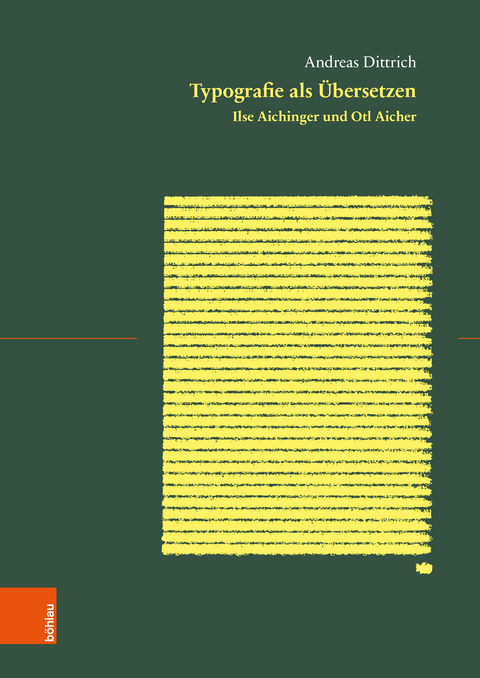
Typografie als Übersetzen
Ilse Aichinger und Otl Aicher
In Otl Aichers Gestaltung der Texte Ilse Aichingers erscheint eine Typografie, die übersetzt.
Das Erscheinungsbild von Ilse Aichingers Texten wird seit 1965 maßgeblich von der typografischen Gestaltung des Bandes »Eliza Eliza« geprägt, die von Otl Aicher eigens entworfen wurde. Dieser Band steht im Zentrum der Untersuchung, in der der Frage nachgegangen wird, wie sich Text und Gestalt zueinander verhalten. Auf Grundlage der in diversen Archiven überlieferten Dokumente wird die Freundschaft der beiden Protagonisten rekonstruiert und die Semantisierbarkeit auch früherer Arbeiten Aichers für Aichinger untersucht. In den eingehenden Analysen der verschiedenen Textgestaltungen erscheint eine Typografie, die weder wesentlicher Bestandteil des Textes ist (visuelle Poesie) noch in einer direkten Inszenierung aufgeht. Was sichtbar wird, ist eine Typografie, die übersetzt.